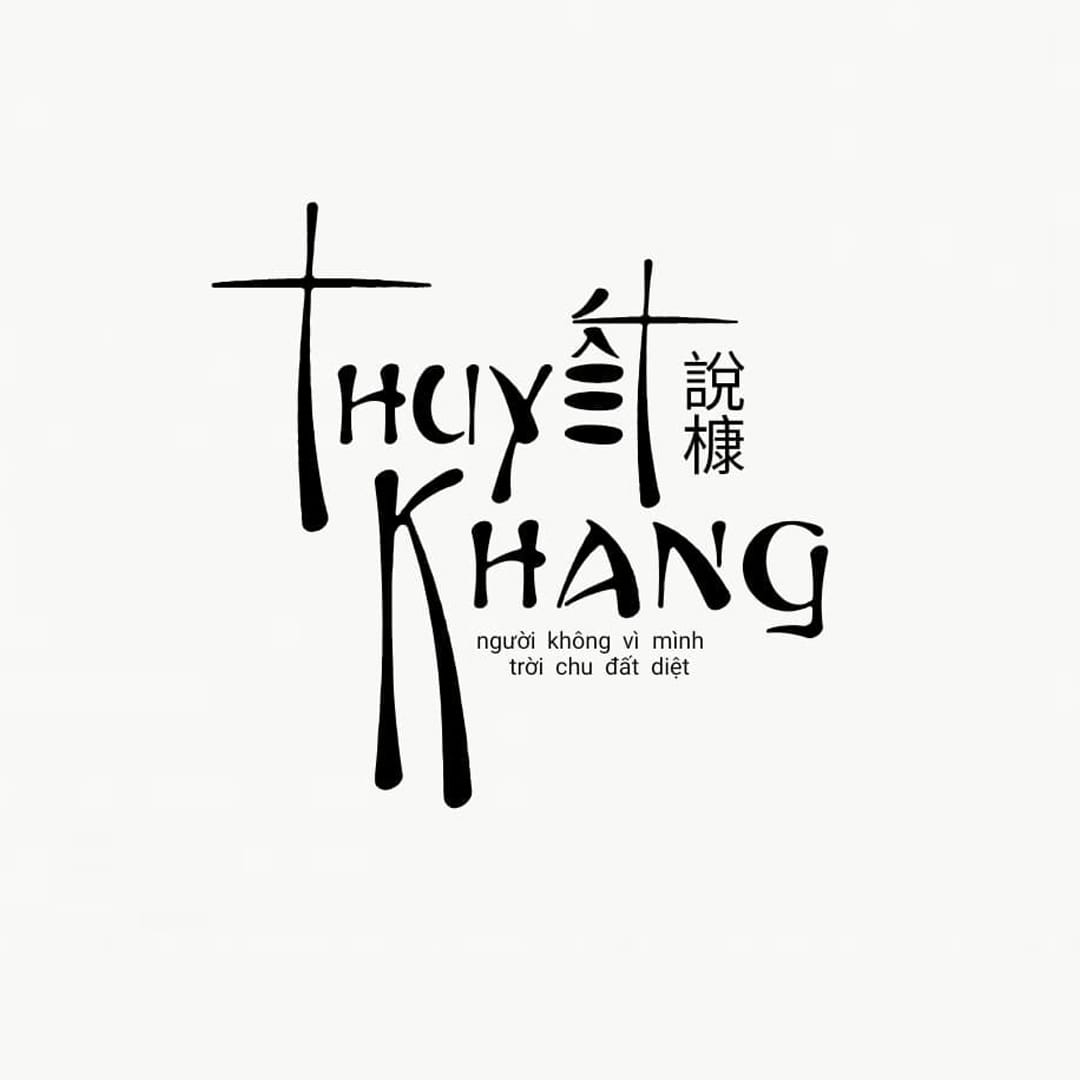
Fontasia Việt Hóa là font chữ dạng thư pháp khá đẹp được thiết kế bởi Walter Velez. Bạn có sử dụng font này trong nhiều thiết kế như bìa sách, poster, biểu ngữ… Cre LNTH
Font Fontasia Việt Hóa – Font thư pháp tuyệt đẹp